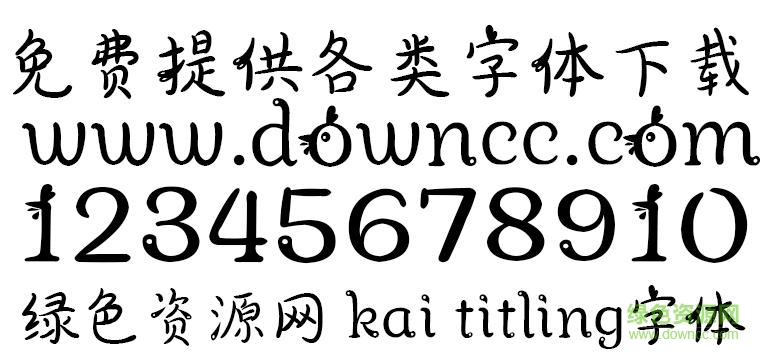
kai titling
kai titling是什么字體?是一款十分好看的英文字體在各項(xiàng)制作中如果使用這款字體能夠顯示出很好的字母與數(shù)字組合效果,十分精美,優(yōu)質(zhì)無(wú)比,小編就很喜歡這款字體呢!
kai titling字體很的獨(dú)特,在字母間能夠展現(xiàn)出很好看的獨(dú)特韻味,能夠適用到各類媒體制作中,同時(shí)如果在廣告設(shè)計(jì)中進(jìn)行使用也將獲得不錯(cuò)效果!